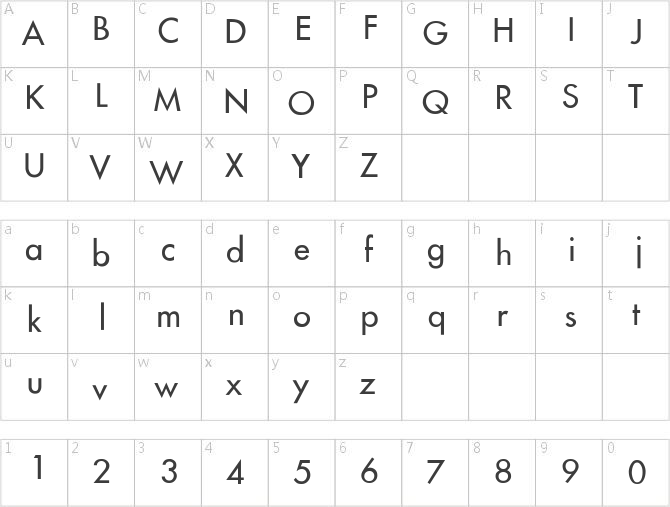
Belmar-Thin 詳情頁
字體名稱: Belmar-
Belmar-Thin
Belmar-Thin介紹
Belmar-Thin字體字庫是一款讓人賞心悅目、百看不厭的英文字體,適合各類廣告和產品包裝設計應用,字體大小0.03MB,格式為ttf字體,上傳用戶是華大文化傳媒,作者/版權方為未知
Belmar-Thin效果圖